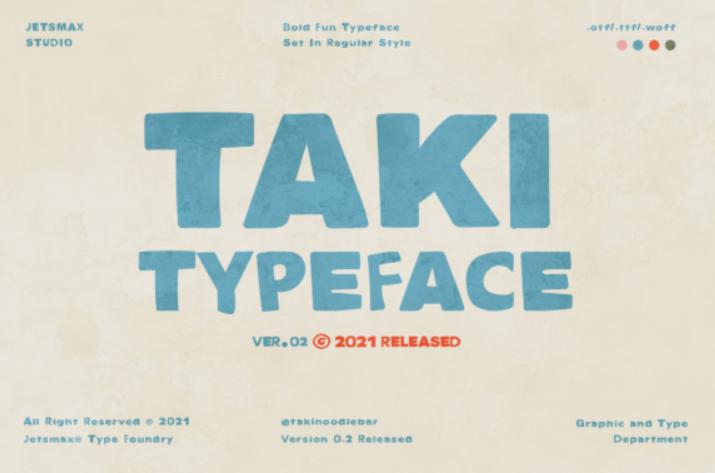
[Creativefabrica] Taki Font (Jetsmax Studio)
Taki - это крутой жирный шрифт в винтажном стиле. Добавьте этот шрифт в свой модный или повседневный дизайн, и вы влюбитесь в результат.